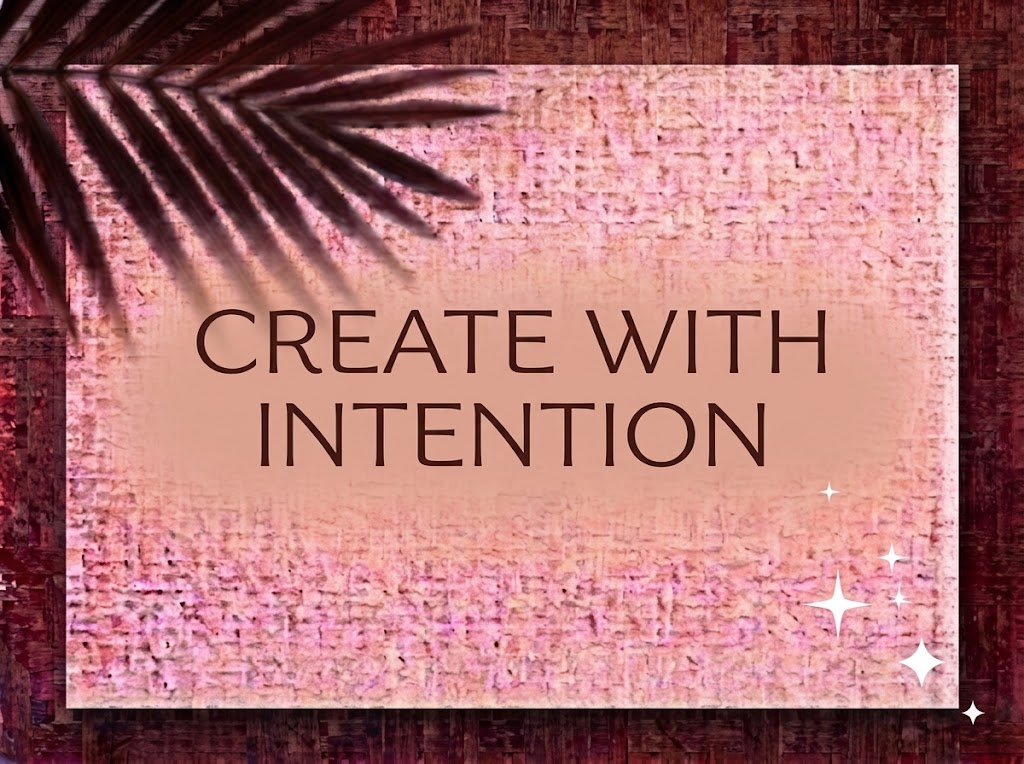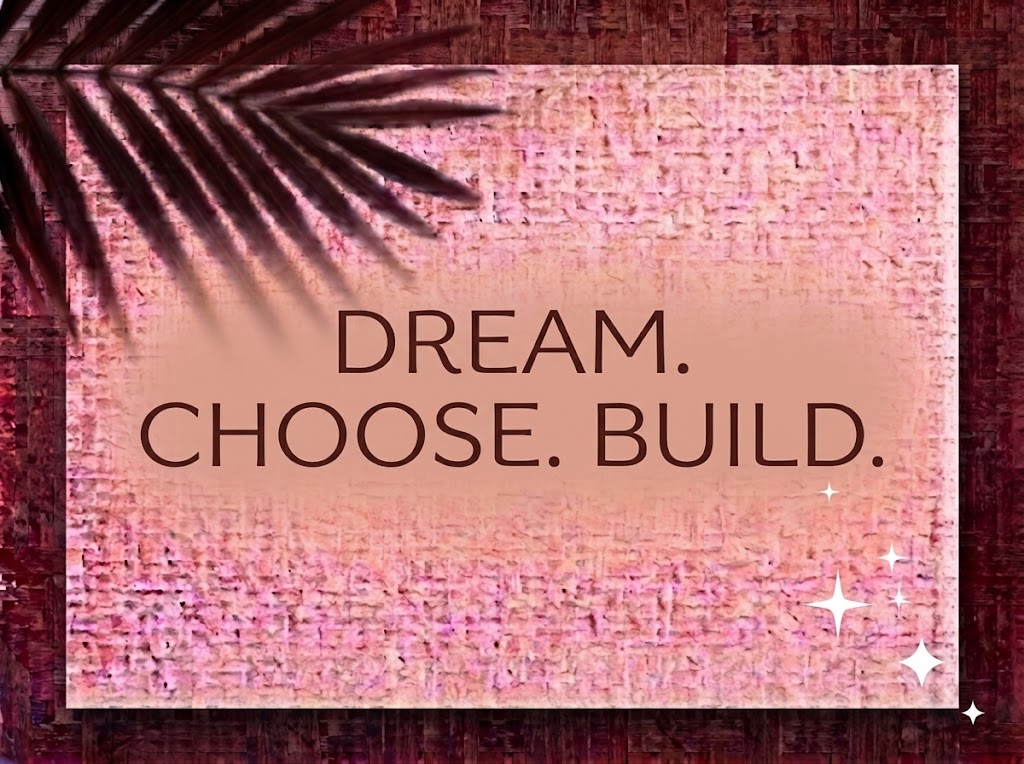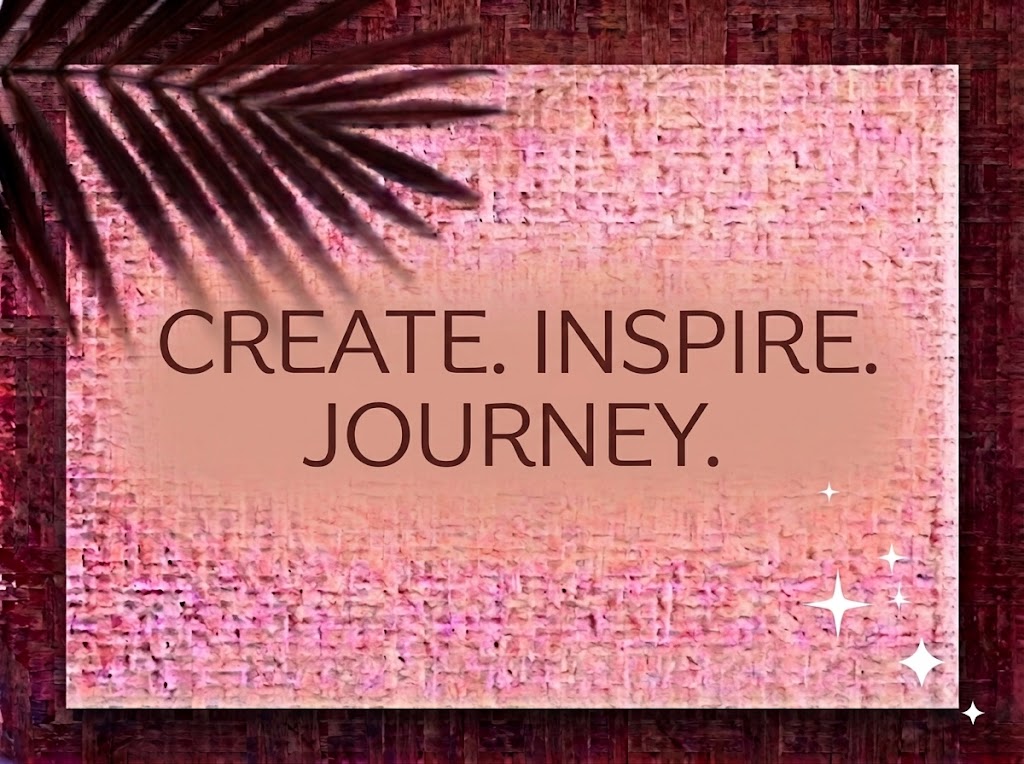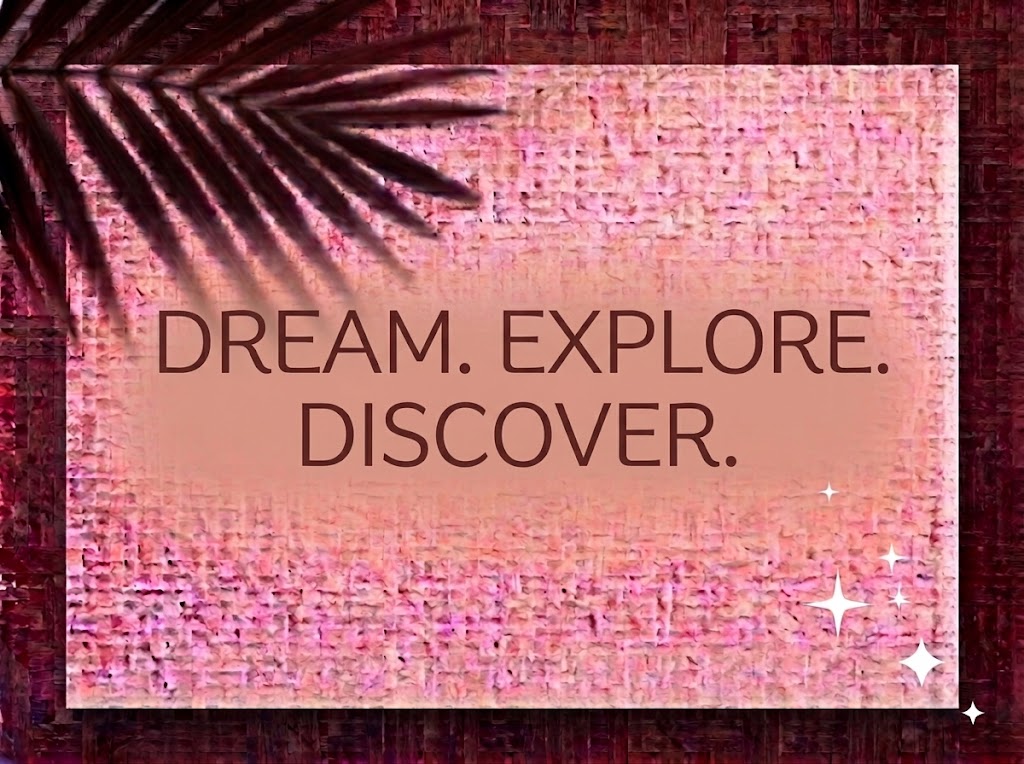
1FTV Konde Light
Trong thiết kế nhận diện thương hiệu và xuất bản đương đại, xu hướng sử dụng các bộ phông chữ không chân (Sans-Serif) kết hợp các nét biến điệu mềm mại đang ngày càng chiếm ưu thế. Sự giao thoa giữa cấu trúc hình học tối giản và những đường cong gợn sóng tinh tế tạo nên một phong cách thị giác vừa hiện đại, vừa giàu chất thơ, mang lại cảm giác nhẹ nhàng nhưng vẫn đọng lại chiều sâu nghệ thuật.
Nếu bạn đang tìm kiếm một phông chữ thanh mảnh, bay bổng để thiết kế bìa sách nghệ thuật, bao bì mỹ phẩm, lookbook thời trang hay tiêu đề video ngắn phong cách aesthetic, font 1FTV Konde Light chính là sự lựa chọn không thể bỏ qua.
Giới thiệu về font 1FTV Konde Light
Tên phông chữ: 1FTV Konde Light
Đặc điểm nổi bật của ngôn ngữ thiết kế Konde Light
Sức hút thị giác của font 1FTV Konde Light đến từ sự tinh tế trong trọng lượng nét cùng các chi tiết tạo hình phá cách độc bản:
Trọng lượng nét thanh mảnh (Light Weight): Nét chữ mảnh mai, thanh thoát mở ra một không gian thị giác thoáng đãng, mang đến tinh thần tối giản (Minimalism) và vẻ đẹp sang trọng, trang nhã.
Chi tiết lượn sóng (Wavy Accents) độc đáo: Điểm nhấn đắt giá nhất của phông chữ nằm ở các nét gạch ngang uốn lượn nhẹ nhàng như sóng nước ở ký tự
f, phần đầu vát mềm ở chữt, cùng nét móc cong duyên dáng ở các chữr,k,j… Chi tiết này thổi vào bộ chữ Sans-Serif khô cứng một linh hồn mềm mại, bay bổng. -
Tỷ lệ khung chữ cân đối: Các ký tự hình tròn như
o,c,e,b,d,p,qđược tạo hình tròn đặn, kết hợp hài hòa với bộ chữ in hoa vững chãi, giúp bố cục dòng tiêu đề luôn giữ được nhịp điệu đọc êm ái và tự nhiên.
Tối ưu hiển thị và dấu tiếng Việt từ 1FTV
Để phông chữ vận hành mượt mà trên cả hai hệ điều hành Windows và macOS, phiên bản này đã được xử lý kỹ lưỡng về mặt thông số kỹ thuật:
Khoảng cách ký tự (Kerning): Khoảng hở giữa các chữ cái được tính toán rộng rãi, thoáng mắt, giúp các chi tiết uốn lượn không bị va chạm hay dính nét vào nhau.
Bản Việt hóa chuẩn chỉnh: Hệ thống dấu thanh tiếng Việt (sắc, huyền, hỏi, ngã, nặng, mũ, móc) được vẽ đồng bộ với độ mảnh của thân chữ, đặt đúng trọng tâm thị giác giúp tổng thể văn bản tiếng Việt giữ trọn vẹn nét thanh tao.
Hệ thống ký tự đồng bộ: Tích hợp trọn vẹn bộ chữ in hoa, in thường, dãy số 0-9 phom dáng thanh lịch cùng đầy đủ các ký hiệu toán học và dấu câu cơ bản.
Đánh giá hiển thị thực tế
Khả năng hiển thị của phông chữ được tối ưu linh hoạt theo nhiều kích cỡ:
Kích thước nhỏ (12pt – 24pt): Cấu trúc chữ thanh mảnh và khoảng mở thông thoáng giúp các đoạn văn ngắn, trích dẫn hay dãy số hiển thị rõ ràng trên màn hình di động.
Kích thước lớn (36pt – 72pt): Đây là đất diễn lý tưởng nhất để 1FTV Konde Light phô diễn toàn bộ nét uốn lượn nghệ thuật, sự kiêu sa và đường cong tinh tế cho các dòng headline chính.
Ứng dụng trong thiết kế đồ họa và sản xuất video
Sở hữu nét cá tính thanh nhã và giàu chất thơ, font 1FTV Konde Light mở ra không gian ứng dụng phong phú:
Video ngắn (TikTok, Reels, Shorts): Dáng chữ thanh mảnh hiển thị rất cuốn hút trên khung hình đứng tỷ lệ 9:16. Cực kỳ phù hợp cho các video aesthetic vlog, podcast chữa lành, phong cách sống tối giản, thơ ca hay nhạc lofi chill.
Ảnh thu nhỏ YouTube (Thumbnail): Lựa chọn hoàn hảo cho các kênh làm nội dung về Lifestyle, kiến trúc nội thất, nghệ thuật cắm hoa, review sách hay âm nhạc acoustic.
Bao bì sản phẩm & Branding Mỹ phẩm: Rất thích hợp làm logo dạng chữ, bao bì sản phẩm chăm sóc da organic, nến thơm cao cấp, nhãn chai nước hoa hay thương hiệu thời trang thiết kế.
Ấn phẩm Editorial & Thiệp cưới: Lựa chọn lý tưởng cho bìa tạp chí nghệ thuật, lookbook, menu nhà hàng chay cao cấp, bảng Welcome tiệc cưới phong cách vintage.